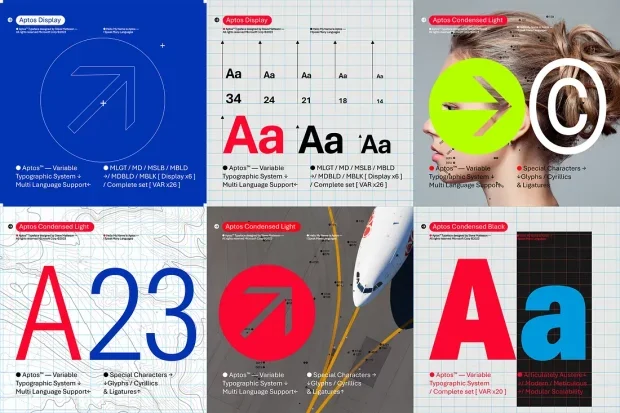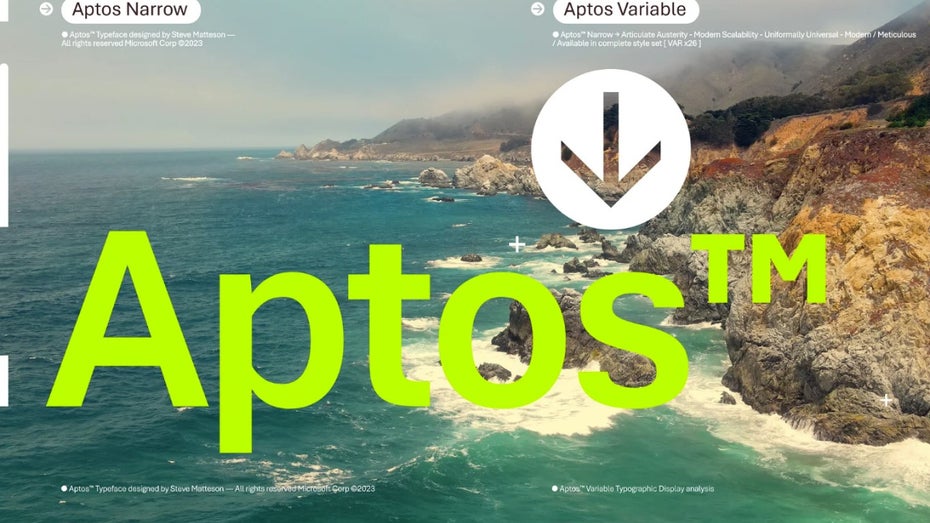
Microsoft ändert den Standard-Font in Office: Tschüss Calibri, hallo Aptos
Eine Ära geht zu Ende und eine neue beginnt: Nach 16 Jahren wird heute der Standard-Font in Microsoft Office von Calibri auf Aptos umgestellt.
Das ist der Calibri-Nachfolger: Aptos, früher bekannt unter dem Namen Bierstadt. (Screenshot:  Microsoft / t3n)
Wie der zuständige Microsoft-Mitarbeiter Si Daniels in einem Design-Blogpost mitteilt, wird heute die seit 2007 verwendete Standardschriftart Calibri in allen Microsoft-Office-Anwendungen durch eine neue ersetzt: Aptos heißt die serifenlose Schriftart, die sich – wie Helvetica – optisch an der Schweizer Typographie Mitte des 20. Jahrhunderts orientiert.
Nach jahrelangem Auswahlverfahren: „Bierstadt“ gewinnt
Vorausgegangen war dieser Veränderung eine jahrelange Suche nach der perfekten Schriftart für einen neuen Abschnitt in der Microsoft-Office-Geschichte. Komplett neu ist Aptos deshalb auch nicht. Unter dem Namen „Bierstadt“ wurde der Font schon 2021 zusammen mit „Grandview“, „Seaford“, „Skeena“ und „Tenorite“ in Windows integriert und damit ins Rennen um den Platz als neuer Standard-Font geschickt. Nach zwei Jahren Feedback ist die Entscheidung jetzt also auf „Bierstadt“ gefallen.
Bei dem Namen handelt es sich nicht – wie man vermuten könnte – um eine Anspielung auf München, sondern um den Namen eines Gipfels in den Rocky Mountains, den Steve Matteson, der Entwickler der Schrift, dadurch ehren wollte.
So sieht der neue Font Aptos aus. (Bild: Microsoft Office)
Zur Feier des Tages gab es dann gleich eine Namensänderung in Aptos, was Bezug auf Mattesons Lieblingsort bei Santa Cruz, Kalifornien, nimmt. Matteson hatte schon Windows-Vista mit einem seiner Fonts ein einheitliches Schriftbild verliehen.
Trotz Aptos-Ablöse: Calibri bleibt erhalten
Jetzt, wo Calibri nach 16 Jahren den gleichen Weg geht wie seine Vorgänger Times New Roman und Arial, findet es sich auch weiterhin bei diesen oben in einer extra Zeile im Schriftauswahlreiter. Ärgerlich dürfte das nur für das US-State-Department sein, denn die Behörde hatte laut The Verge erst kürzlich verfügt, dass alle Dokumente in Calibri verfasst sein müssen.
Aptos wird weiterhin zusätzlich unter dem Namen „Bierstadt“ auffindbar sein. Die Änderung betrifft alle Microsoft-Office-Programme, also Word, Outlook, Power Point und Excel. Microsoft hat noch einige weitere Änderungen für Office 365 geplant, um die Anwendungen inklusiver und leichter benutzbar zu machen.